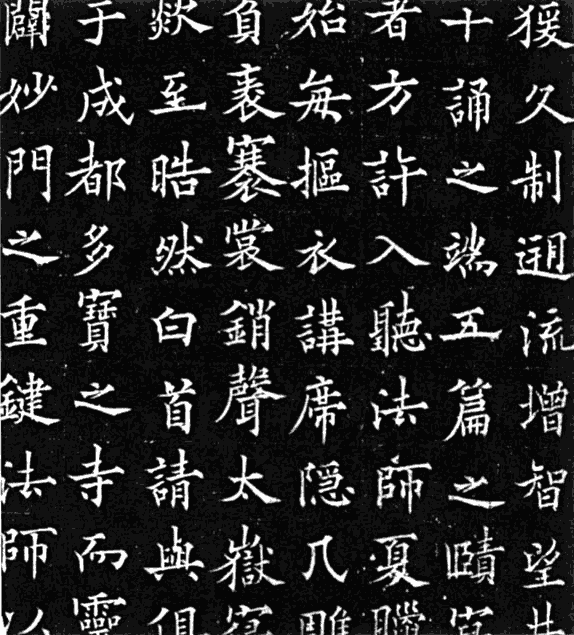
欧阳通
欧阳通简介
字通师,潭州临湘(今湖南长沙)人,欧阳询第四子,少夫人徐氏出。官兰台令,仪凤中累迁中书舍人,封渤海公,天授初转司礼卿判纳言事,二年为相,因反武承嗣为太子被害。
欧阳询去世时,欧阳通尚年幼。母徐氏盼子继承父业,亲自督教书法。那时其父亲的手迹大多散存于民间,徐氏不借以重价购回。欧阳通朝夕临摹,书法大进,尽得父法。遂与其父有“大小欧阳”之称。其书隶意更浓,然而锋颍过露,含蓄处不及其父。晚年颇有矜重,以狸毛为笔,覆以兔毫,犀象骨做管。南宋董卣《广川书跋》评其书:“笔力劲健,尽得家风,但微伤丰浓,故有愧于父。至于惊奇跳骏, 不避危险,则无异也。”其传世作品有《道因法师碑》、《泉男生基志》等。
《道因法师碑》
《道因法师碑》,李俨撰,欧阳通书,现收藏於西安碑林。碑全文楷书,三十四行,满行七十三字。高 312厘米,宽 103厘米。为唐高宗龙朔三年(公元 663年)建。碑文完整无缺,碑头雕作螭首,碑额处雕饰佛瞰,瞰下横书“故大德因法师碑”七字。
道因法师俗姓侯原出家成都多宝寺,唐贞观年间,曾在长安大慈恩寺协助玄奘翻译佛经,因而碑文首题有“翻经大德”之句。龙朔三年(公元663),他的弟子玄凝请欧阳通书立《道因法师碑》来纪念他。
欧阳通学书时期,正当初唐书法发生变化的时期,而他以“善学父书”著称。此碑笔力劲健,有隶意含蓄处不及其父,方笔侧入笔法更增加峭险之势,古人反对者多,与中国重涵蕴美德有关联。何义门说:“兰台《道因碑》肩吻太露横,往往当收处反飞。”王世贞说:“此碑如病维摩,高格贫土,虽不饶乐,而眉宇间有风霜之气,可重也。”
唐  欧阳通 道因法师碑 大唐故翻经大德益州多宝寺道因法师碑文并序
唐 欧阳通 道因法师碑 宋拓
宋拓 唐道因法师碑
唐 -欧阳通 道因法师碑 宋拓